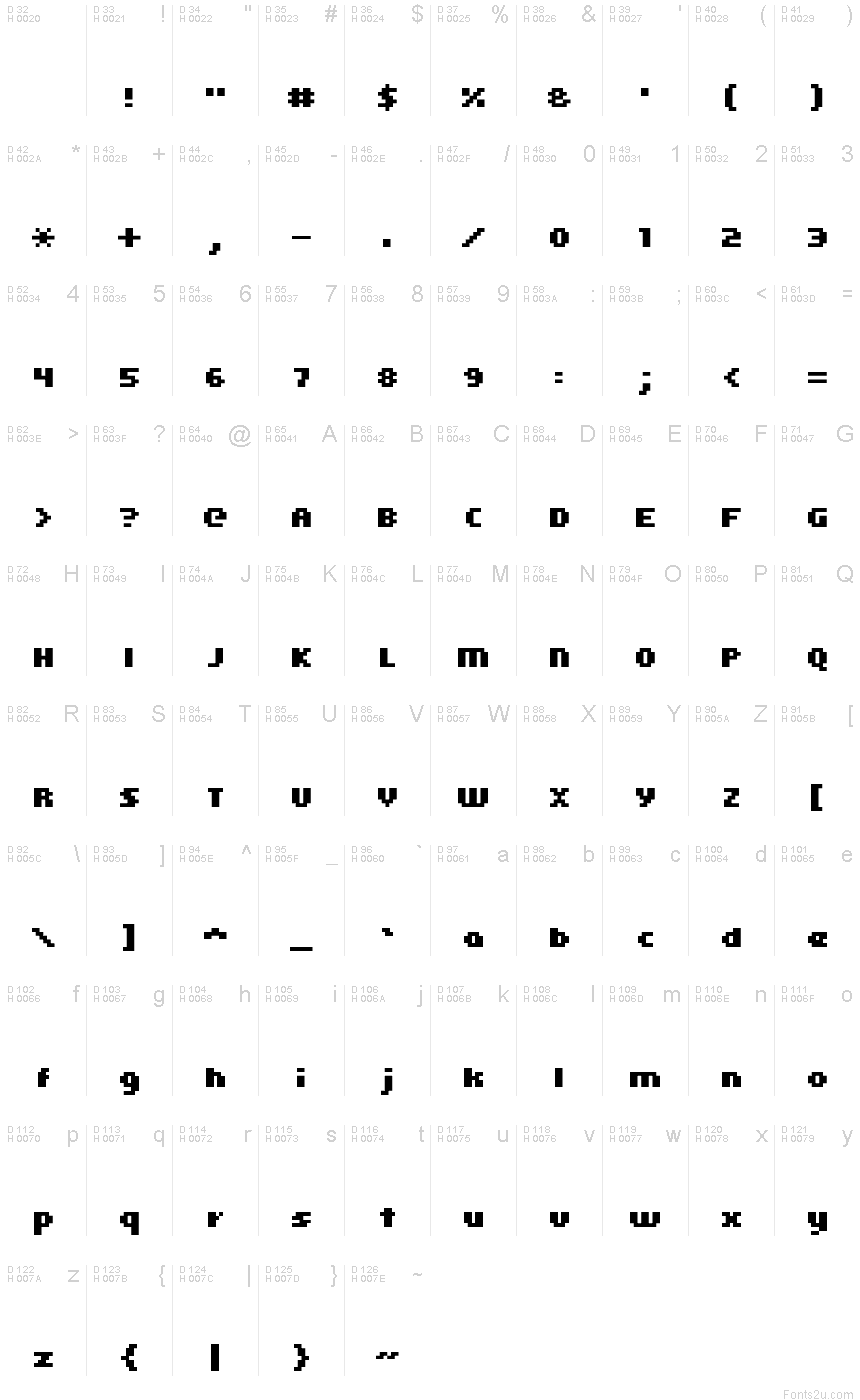
Kroeger 05_65, darmowy font bitmapowy w stylu pixel art autorstwa Craiga Kroegera z 2002 roku, oddaje surowy klimat gier komputerowych i wczesnych systemów desktopowych. Litery zbudowane są z masywnych kwadratowych modułów i ciasnych kątów prostych, co nadaje krojowi suchy, mechaniczny rytm – sprawia wrażenie wygenerowanego kodem, a nie narysowanego odręcznie.
Idealnie pasuje do grafik w stylu retro, plakatów nawiązujących do oprogramowania, zinów, ikon webowych oraz krótkich nagłówków, gdzie charakterystyczna, kanciasta siatka mówi sama za siebie. Jako darmowy font, świetnie sprawdzi się również w kompaktowych logotypach, menu i tekstach z interfejsem w roli głównej, szczególnie gdy szukasz sztywnej, cyfrowej tekstury zamiast gładkich krzywizn.